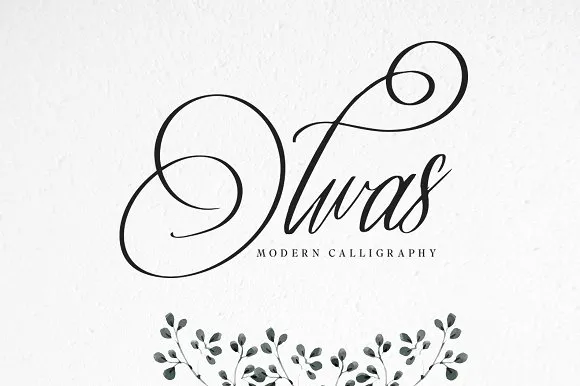
Olwas Script Font é uma elegante tipografia moderna criada por 178-MC para a categoria de fonts script na CreativeMarket. Este é um font premium que oferece uma ampla gama de recursos, incluindo letras maiúsculas e minúsculas completas, pontuação variada e números. Conhecida por sua beleza, Olwas Script se adapta perfeitamente para logotipos, cabeçalhos de sites, design de moda e até mesmo cards de casamento. Com seu estilo elegante contendo tanto um Olwas font como uma fonte Italic, é ideal para a criação de ambientes sofisticados que transmitem beleza e delicadeza. Se você está buscando adicionar uma nota única e profissional aos seus projetos de design, vale muito a pena experimentar Olwas Script Font.